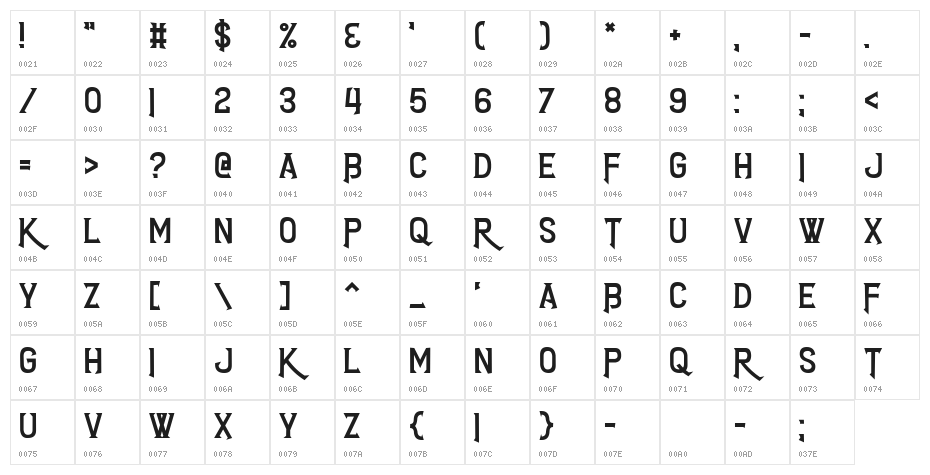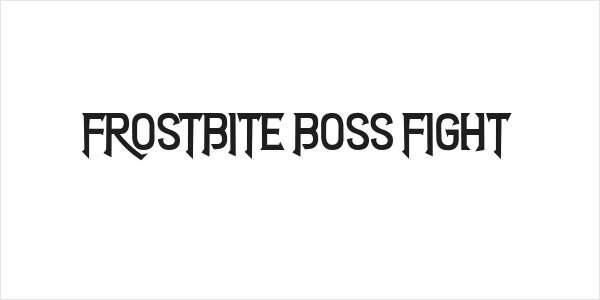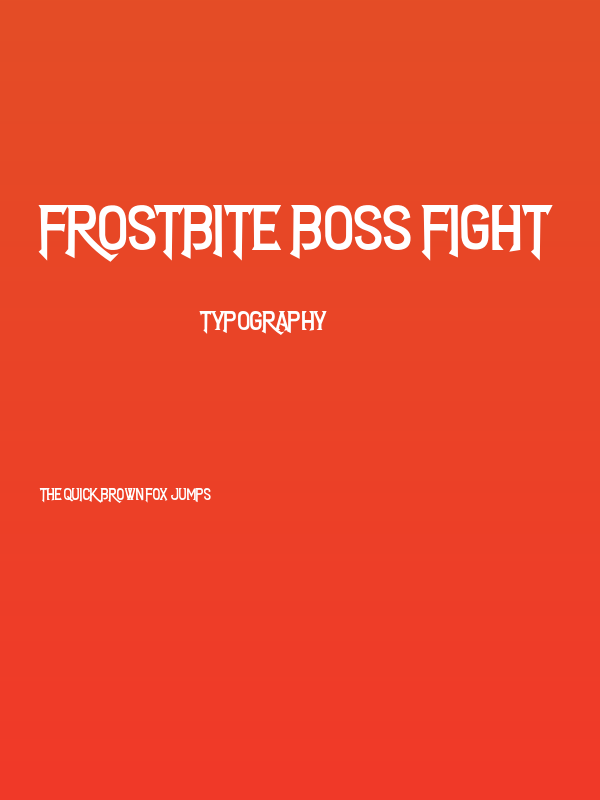
Frostbite Boss Fight Font
✎ Thick
| Kategorien | Thick |
| Gesamtstil | Modern, Edgy |
| Vorgeschlagene Projekte | This font is perfect for projects that require a strong visual impact, such as posters, logos, video game titles, and branding materials. |